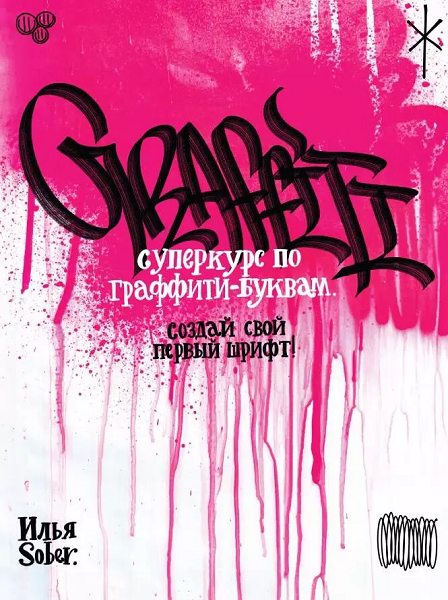
Суперкурс по граффити-буквам. Создай свой первый шрифт! [Илья Sober]
Илья Собер / Sober — граффити-художник с 12-летним опытом, инфлюенсер, основатель собственной творческой мастерской и создатель коллекции граффити-мерча. Его уличные работы можно встретить в России, Дубае, Бали, Шри-Ланке и Таиланде, а картины находятся в частных коллекциях в 18 странах мира. За время своей работы Илья успел посотрудничать с блогерами, ивент-агентствами и брендами от бьюти-бизнеса до телеканалов.
Вся его жизнь пропитана творчеством, и в этой книге он готов поделиться техниками и идеями для создания удивительных надписей в стиле граффити.
Перед вами — уникальное творческое пособие для тех, кто хочет обучиться основам граффити-искусства — направлению, стремительно набирающему популярность по всему миру.
"Суперкурс по граффити-буквам" позволит вам с головой окунуться в мир эстетики букв и медитативного спокойствия. Базовые знания, которые предлагаются в этой книге, будут хорошим фундаментом, на который вы сможете легко наслаивать свой новый опыт и совершенствоваться. Вы изучите основные стили создания и соединения букв и создадите свои первые работы. Теория и практические советы, представленные в книге, пригодятся не только начинающим художникам, но и всем творческим людям, работа которых связана с индивидуальным и креативным подходом в различных областях.